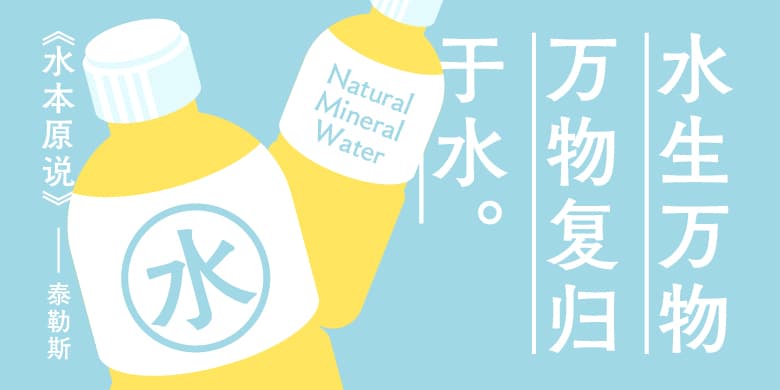
这是一款全新设计的黑体,却能给人在金属活字时代存在过的一种似曾相识感。保持了筑紫字体系列「文字内涵信息丰富」的优点。在所有筑紫字体中这款字的信息量最大,文字本身就能洪亮地发声。横竖笔画都加上了有机的抑扬顿挫,而进一步收紧的中宫让其成为最富有情趣的黑体。单用汉字排成词句,与其他字体的区别便一目了然。